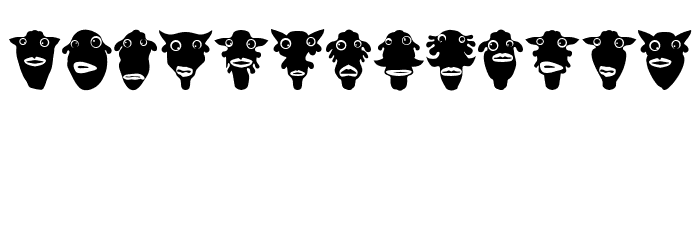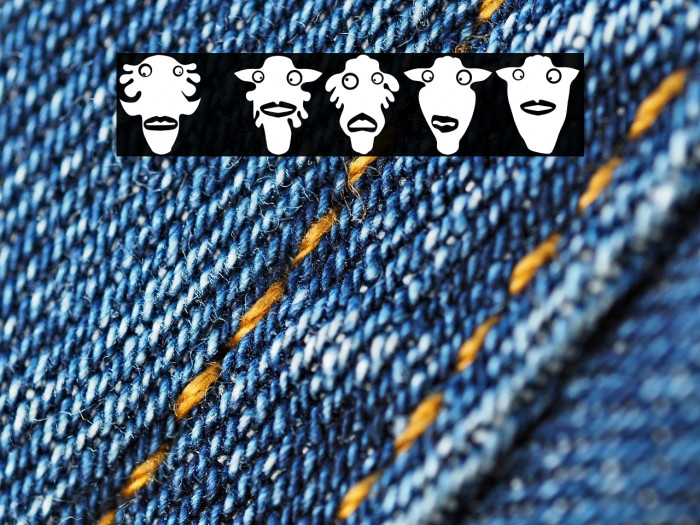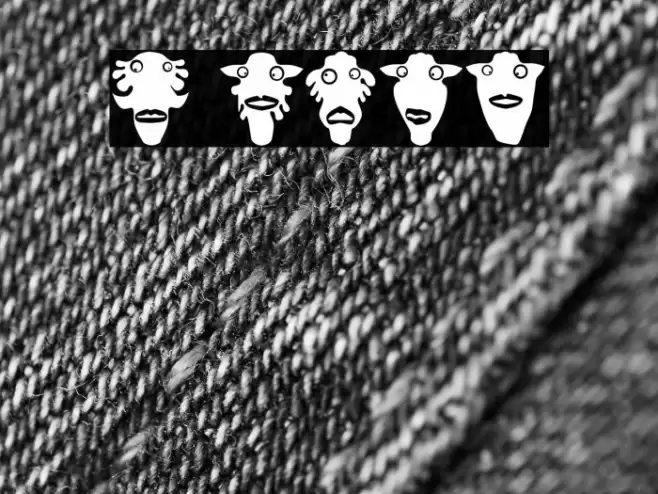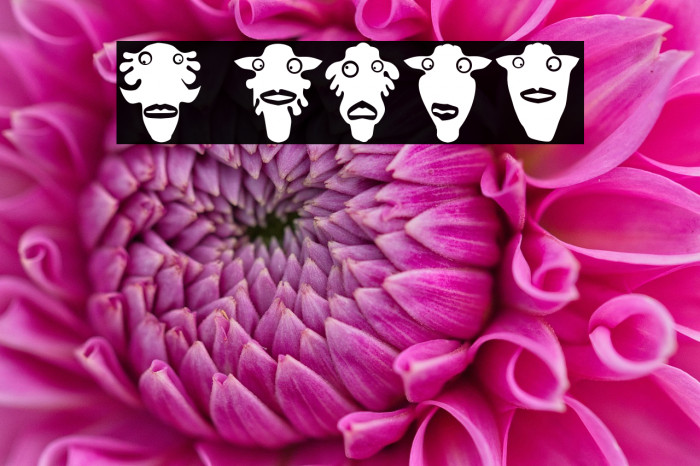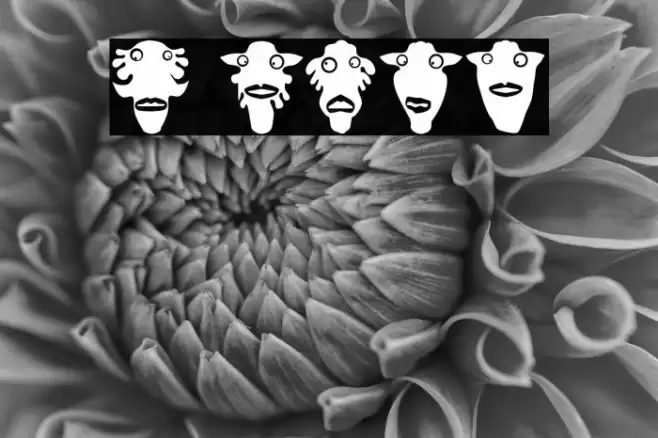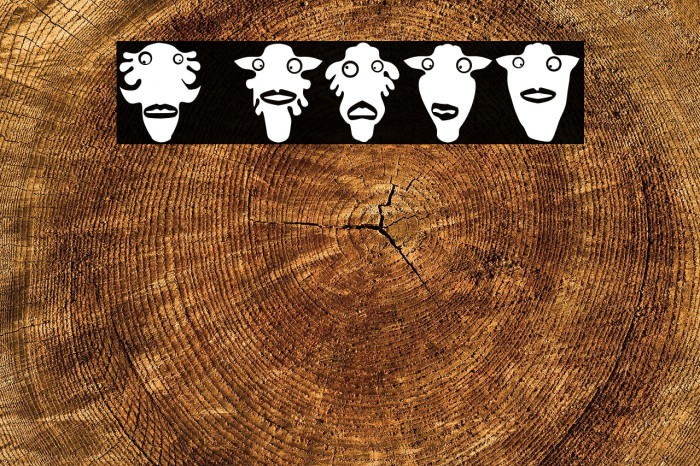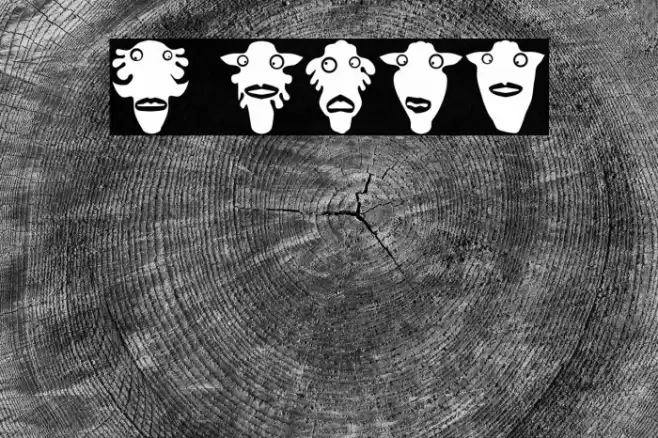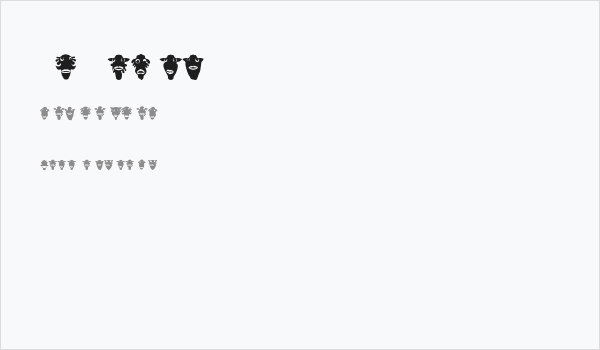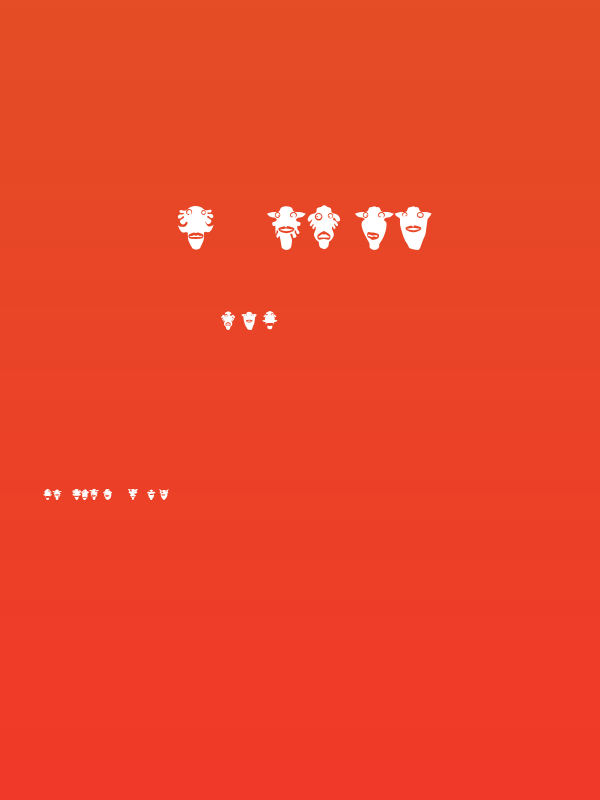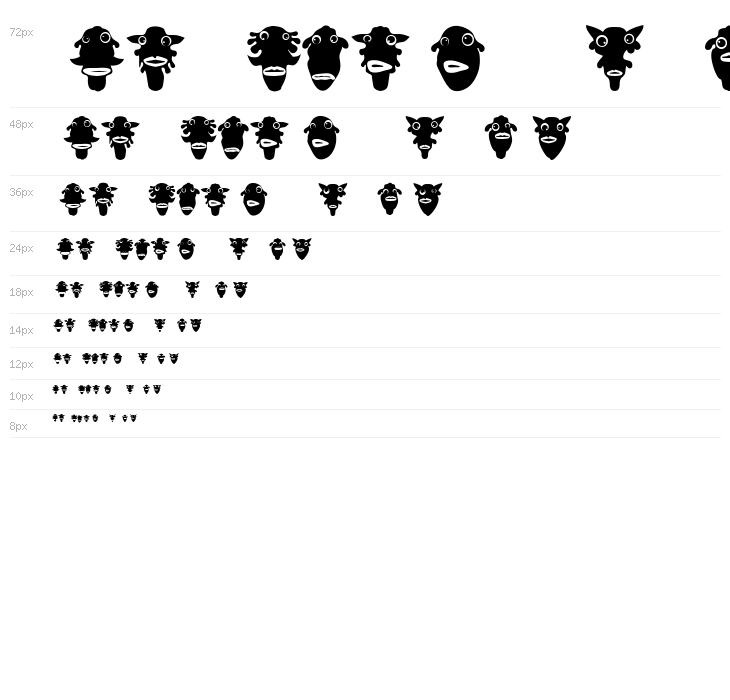
Prins Regular Font
| Estilo general | Whimsical, Playful, Decorative |
| Caso de uso | Logos, Headlines, Themed graphics, Posters |
| Proyectos propuestos | Children’s books, farm-themed posters, playful branding, party invitations, educational materials. |